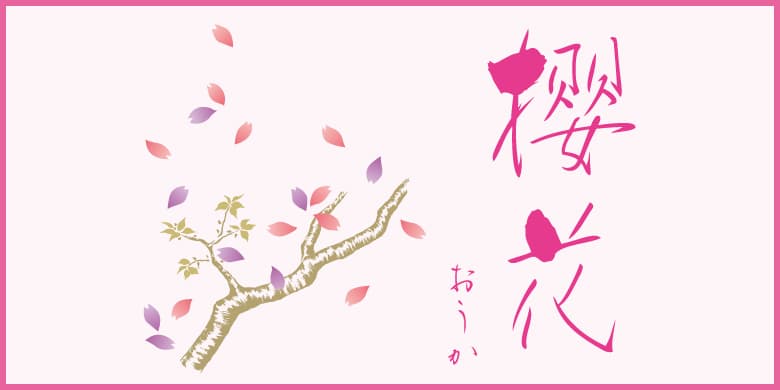
方正白舟樱花体
品牌:方正字库设计师:株式会社白舟书体发行时间:2021字库编码:大陆简体(GB2312-80)分类:创意书写字体属性:精品字
“樱花”虽然不是正统的行书,但是流畅的极细线条让字体呈现出别样的美感;笔迹精美,每个汉字都包含一笔线条较粗的点状笔画,象征着樱花的花瓣。
这款字体由书法家来住和子书写。